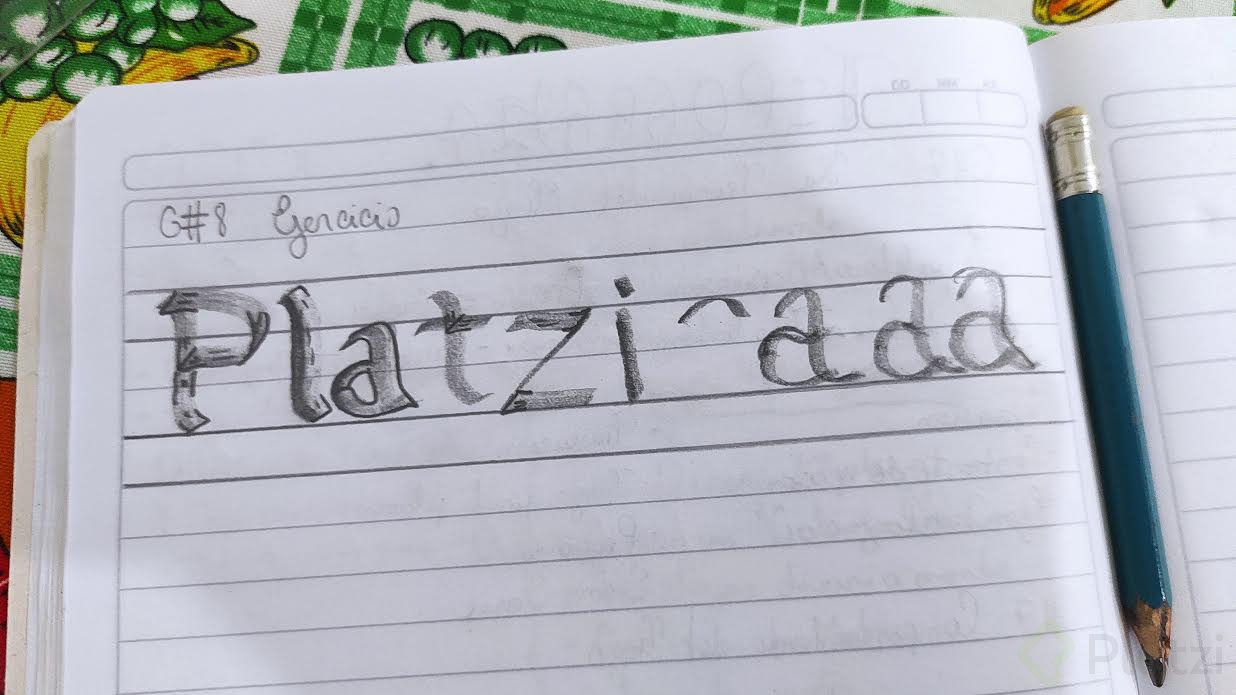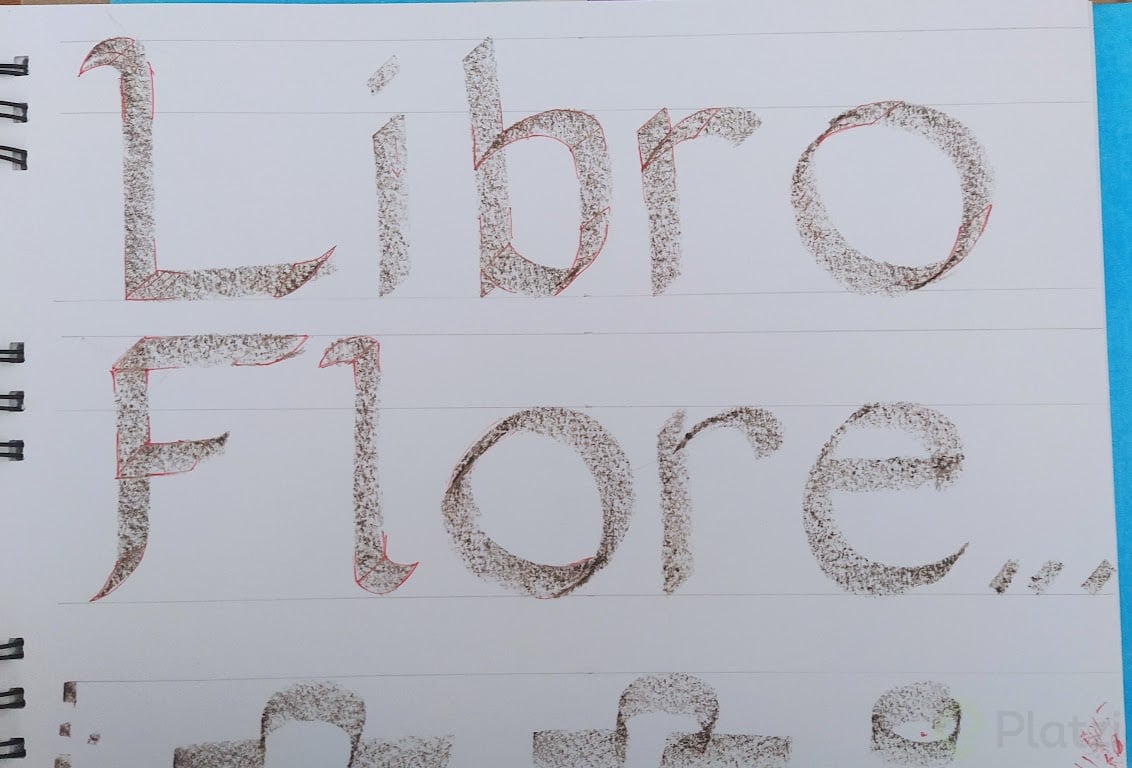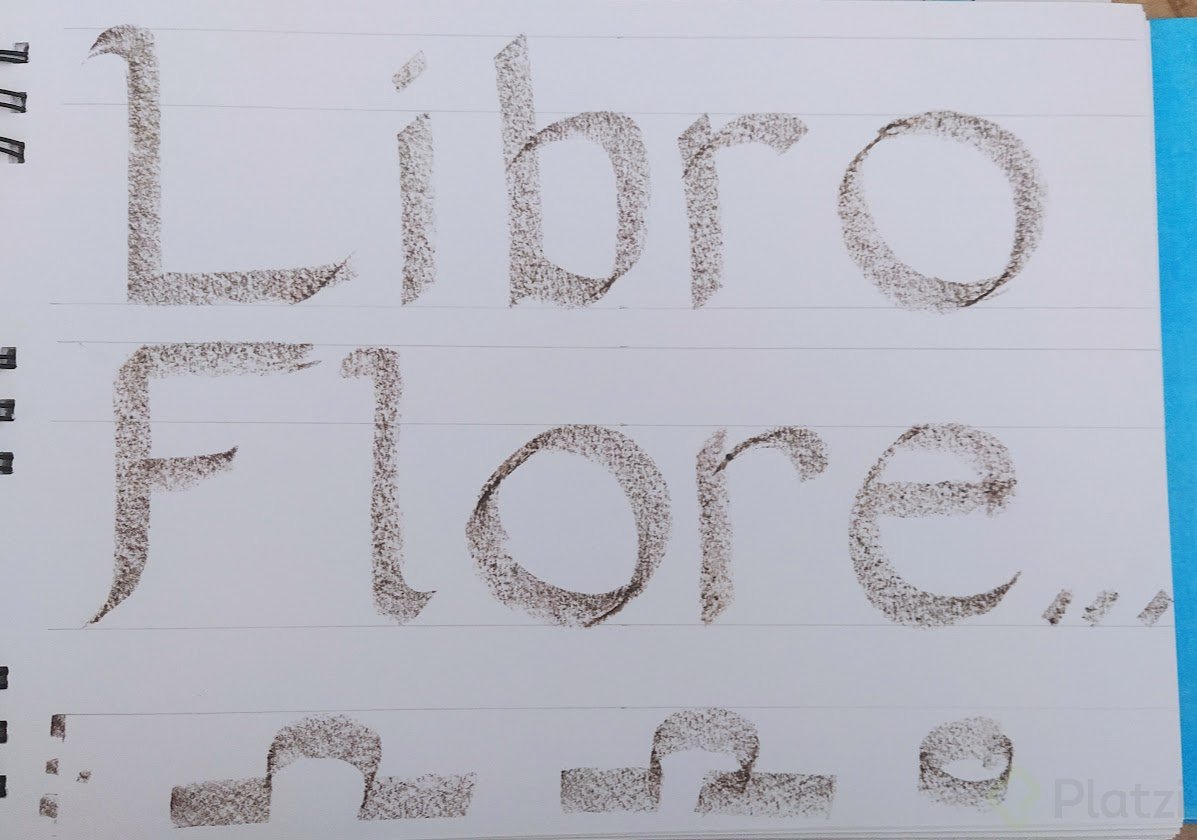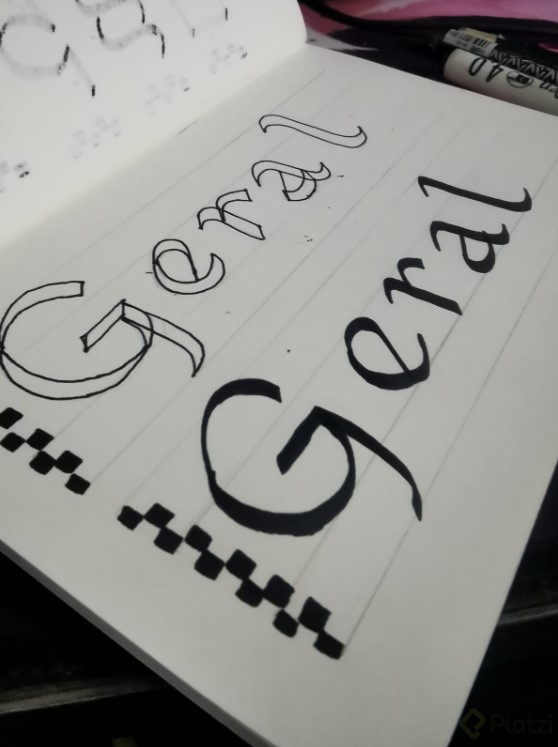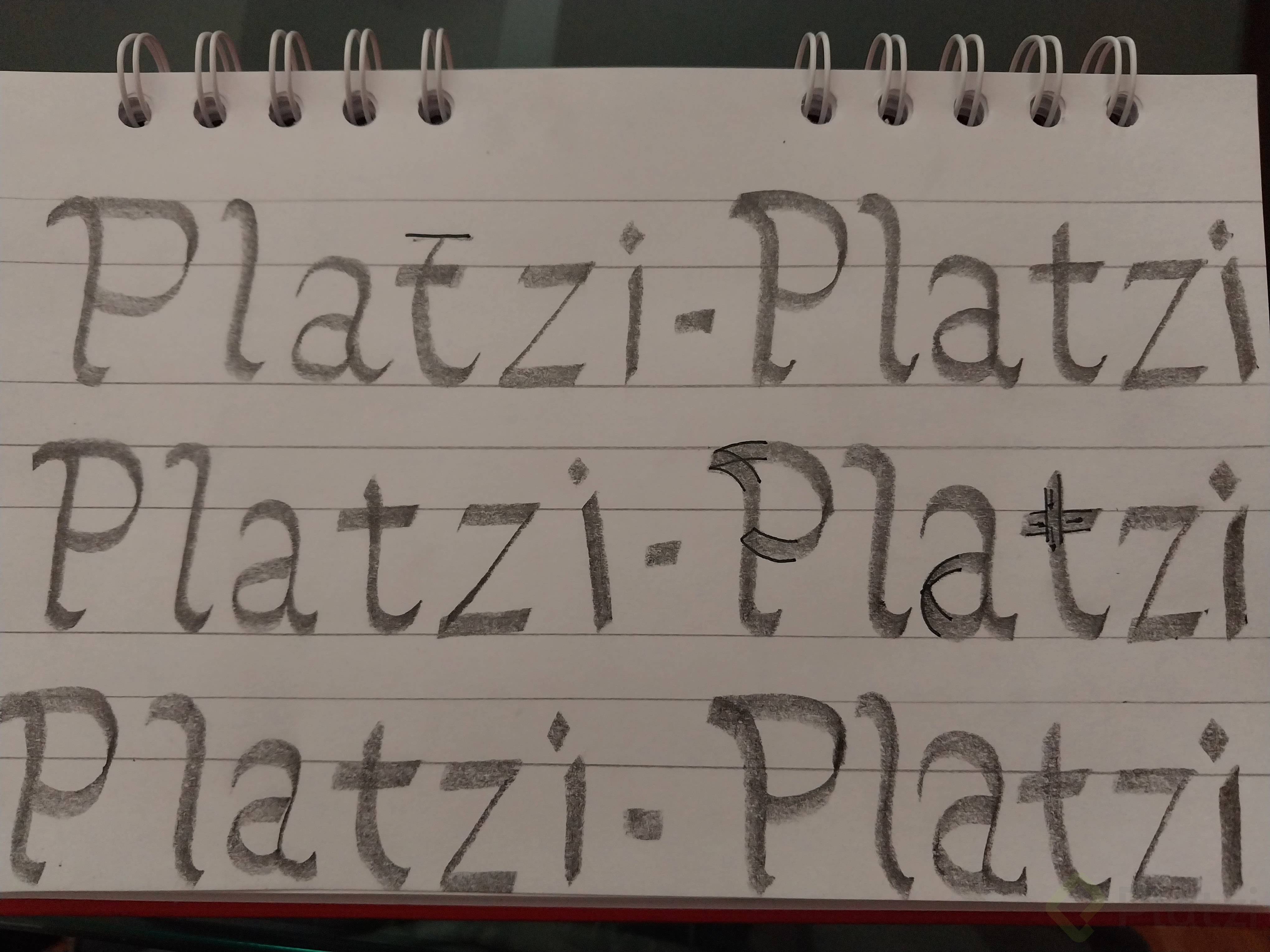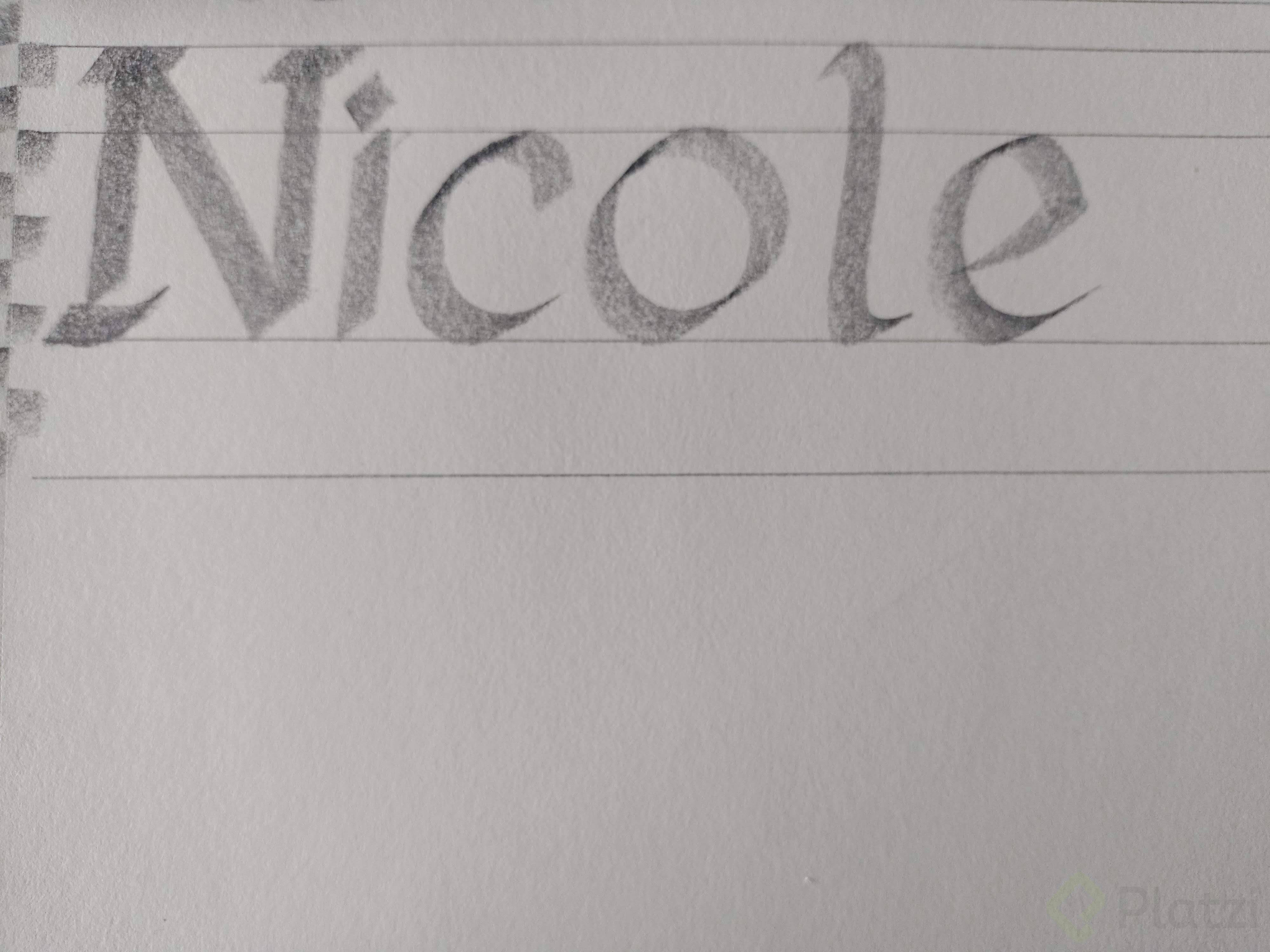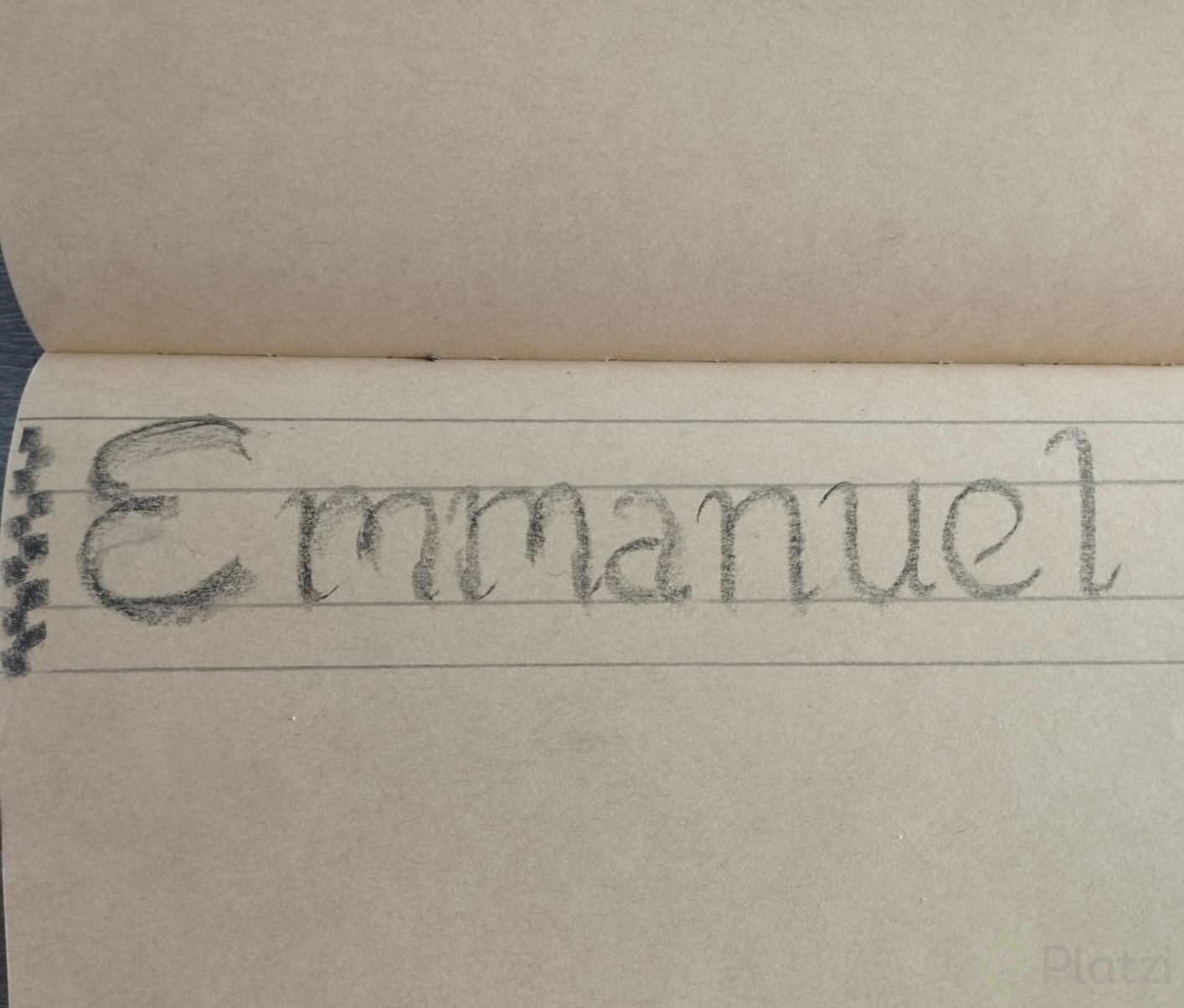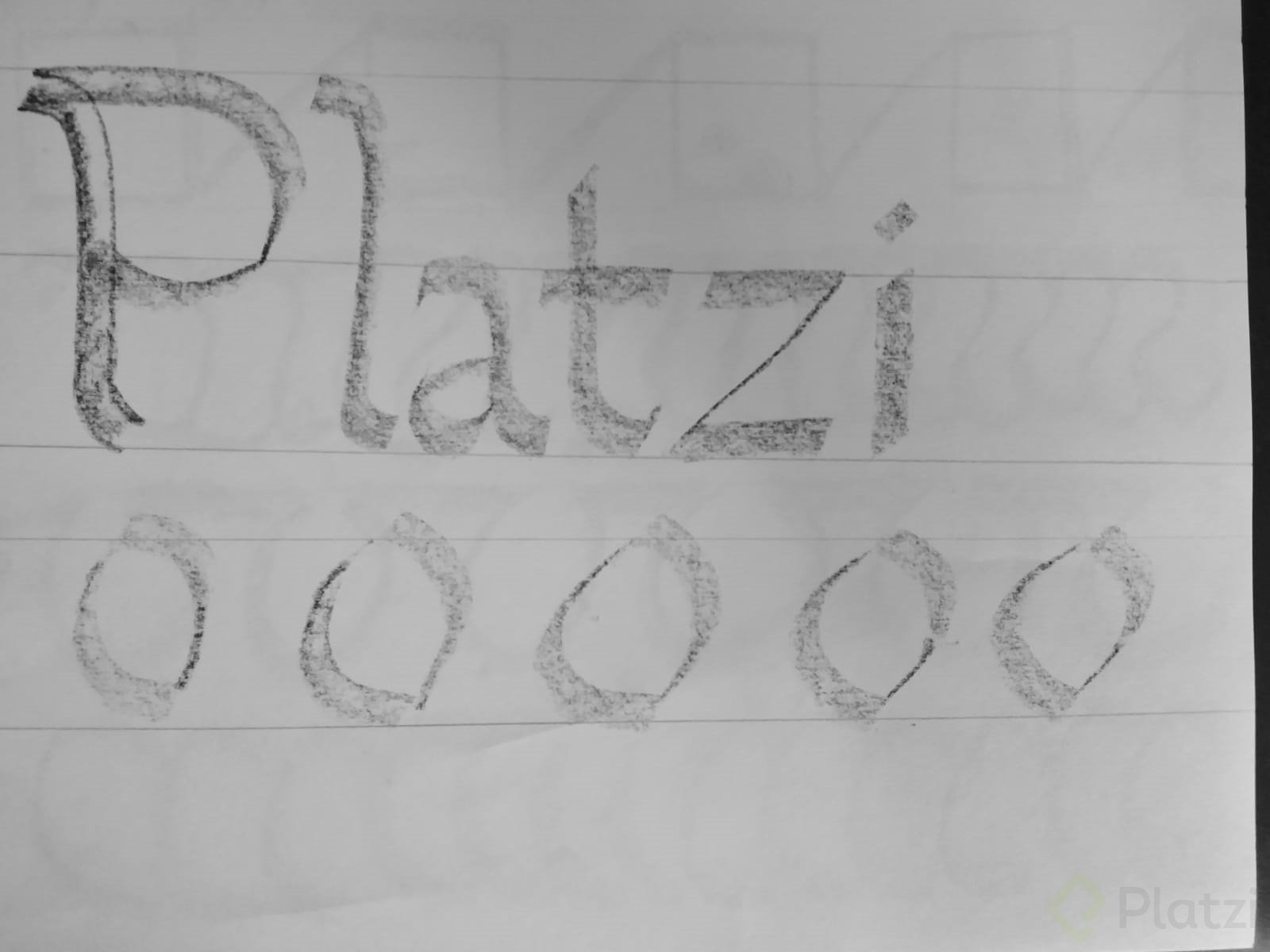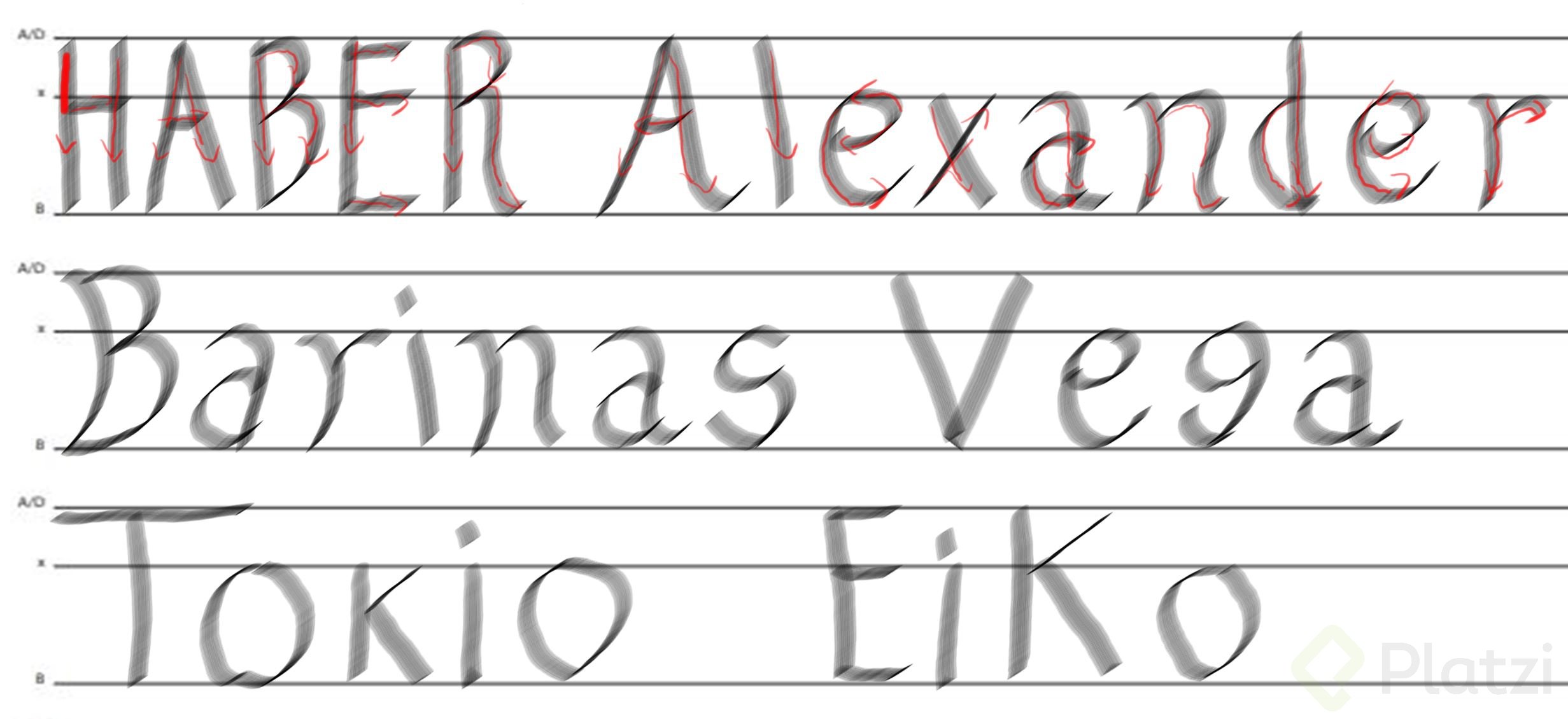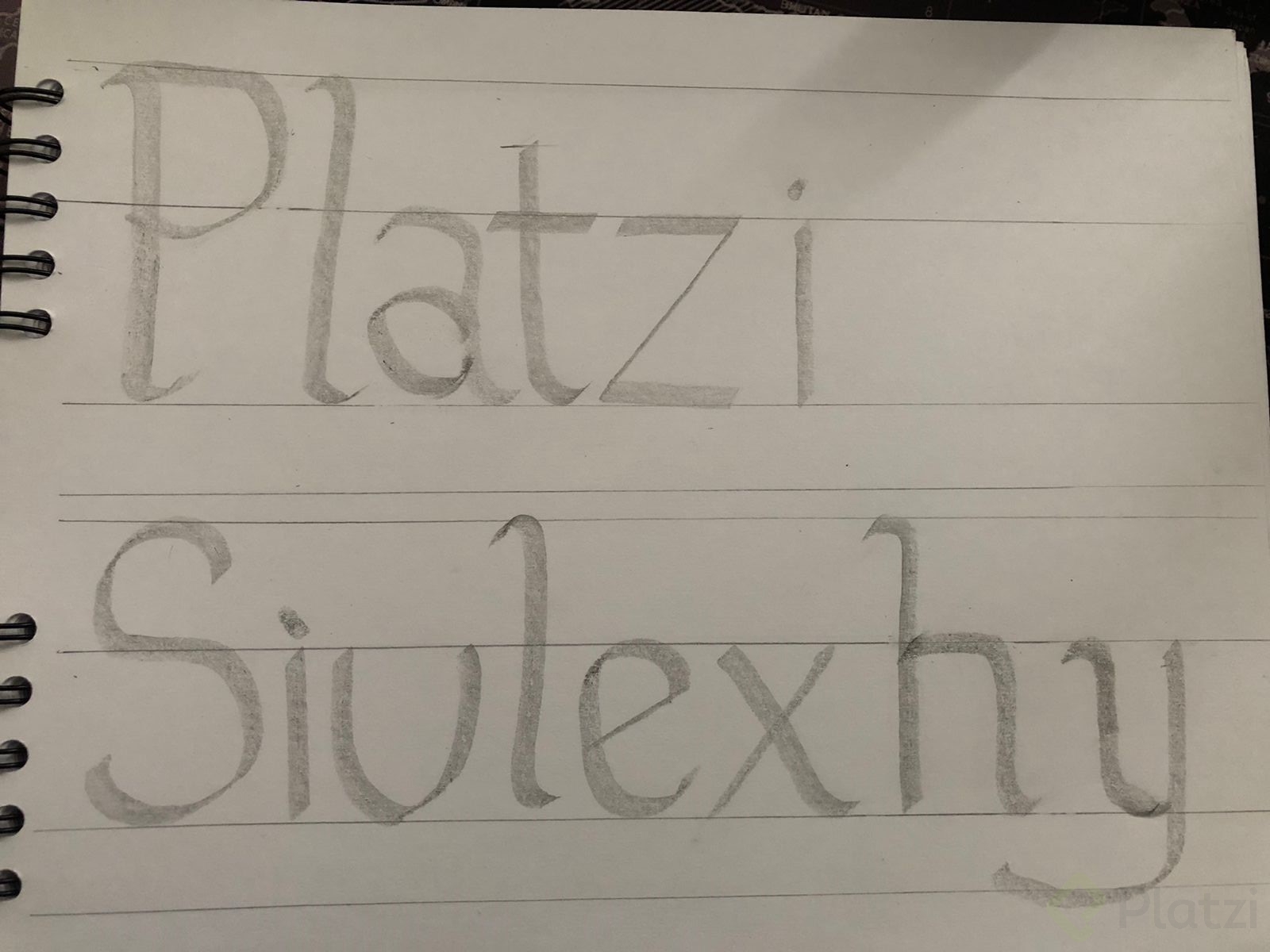
Ejercicio práctico, comportamientos del trazo
La caligrafía es un arte que combina precisión técnica y expresión artística.
Identificar los comportamientos del trazo permite mejorar nuestras habilidades y profundizar en el diseño y la ejecución de las letras.
1. ¿Qué es un renglón caligráfico y por qué es importante?
El renglón caligráfico es una guía visual esencial para organizar y estructurar las letras.
Define las áreas clave donde las letras se desarrollan, asegurando proporción y consistencia:
- Altura de mayúsculas: espacio dedicado a las letras mayúsculas.
- Altura de la X: área donde se sitúan las minúsculas, excluyendo trazos ascendentes o descendentes.
- Línea base: línea donde descansan las letras, proporcionando estabilidad.
- Altura de letras descendentes: espacio ocupado por los trazos que se extienden debajo de la línea base.
Usar correctamente estas guías facilita la ejecución de trazos uniformes y estéticamente agradables.
2. ¿Cómo aplicar los comportamientos del trazo al escribir letras?
Controlar y aplicar diferentes tipos de trazos es clave para dominar la caligrafía.
Aquí se explican algunos elementos esenciales:
Letras mayúsculas y minúsculas:
- Ejemplo: Escribir la palabra "Platzi".
- La P mayúscula comienza con un trazo curvo que desciende en línea recta.
- Las letras minúsculas como l y a deben mantener proporciones precisas dentro de la altura de la X.
Trazos esenciales:
- Rectos y curvos: forman la base de las letras. Por ejemplo, la curva de la P o la línea recta de la T.
- Uniformidad: integrar tridimensionalidad en puntos clave, como la transición en curvas o vértices.
Conexiones y empalmes:
- Ejercita las transiciones suaves entre trazos.
- Ejemplo: en la P, el trazo curvo de la barriga debe conectarse perfectamente con el trazo vertical.
Esqueleto básico:
- Construye la estructura primaria de las letras antes de añadir detalles.
- Esto asegura proporción y equilibrio.
Tridimensionalidad:
- Aplica efectos de volumen en trazos horizontales o transversales, como en la barra de la T, usando ángulos y modulaciones precisas.
3. ¿Cómo mejorar la conexión entre el cerebro y la mano?
El arte de la caligrafía también fortalece la relación entre mente y cuerpo, mejorando la precisión y la atención al detalle.
Prácticas clave:
- Observación crítica: examina tus trazos para identificar áreas de mejora, como inconsistencias en grosor o curvas.
- Perspectivas adicionales: cambia herramientas o ángulos de inclinación para enfrentar nuevos desafíos y enriquecer tu técnica.
- Ejercicio constante: practicar regularmente, consolida tus habilidades y mejora tu percepción del diseño caligráfico.
Ejemplo del ejercicio realizado por la estudiante Mariana Gil Madrid.
La caligrafía es un viaje que combina técnica, creatividad y disciplina.
Al comprender los comportamientos del trazo y practicar con constancia, mejorarás tanto tus habilidades como tu conexión con este arte.
¡Sigue explorando y disfrutando de la belleza de la escritura! 😊